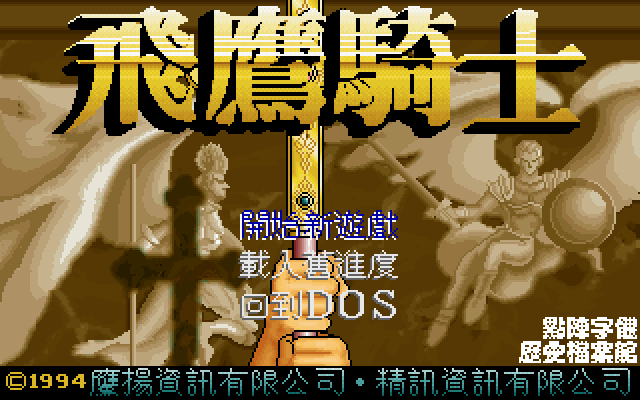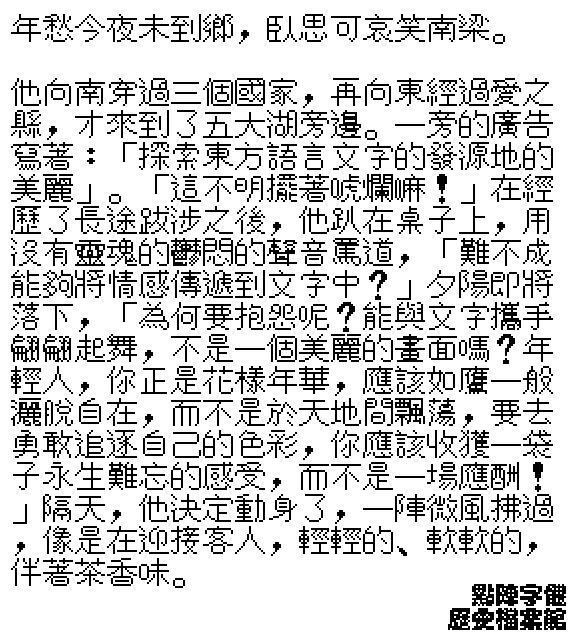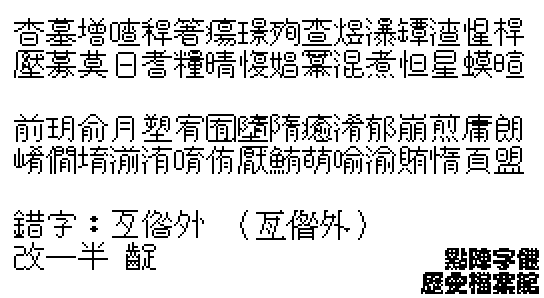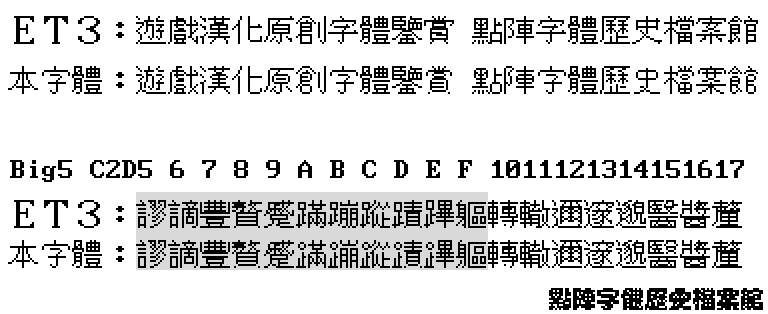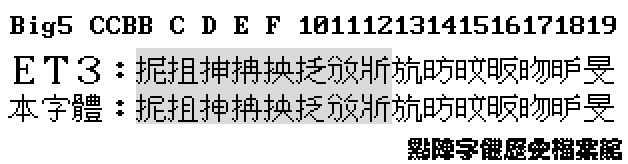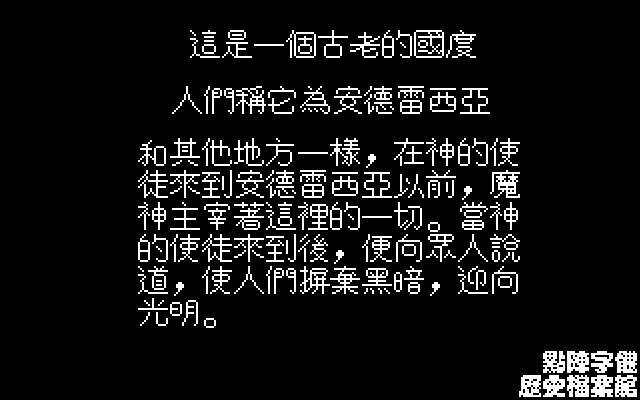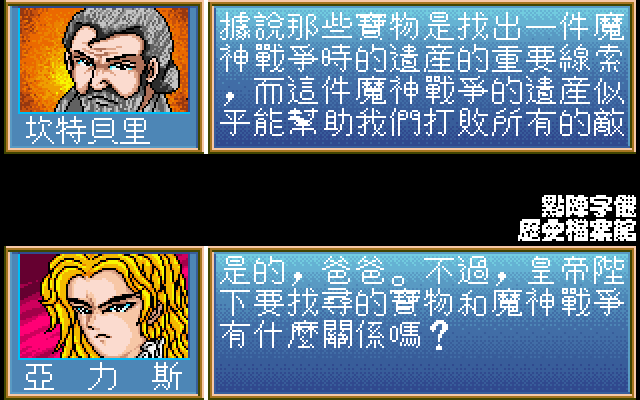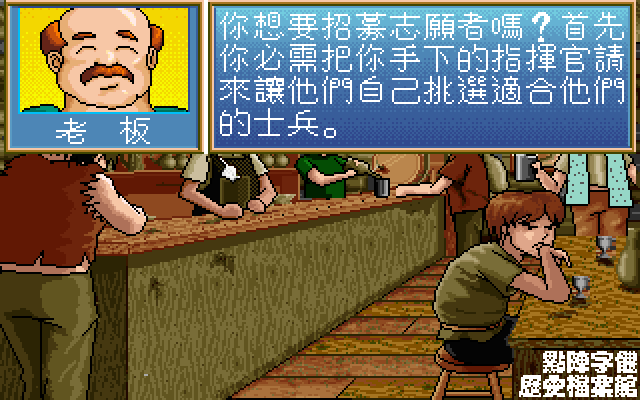
早安,這是小型欄目《遊戲漢化原創字體鑒賞》,關注於早期只在遊戲漢化中出現的點陣字體。
此欄目第三款要介紹的字體,是鷹揚/精訊於1994年後推出的漢化或原創遊戲所採用的字體。風格上是至今都少見的16Px圓體。
圖:採用此字體的遊戲。
猜測這款字體在誕生之初就是在該公司的所有產品上使用,所以一經亮相就是可廣泛使用的狀態了。該字體整體感覺偏扁,常用字中能展現圓角的地方幾乎都弄了,特別是日、目、月等字選擇橫不接豎也為字體增添了特色。可惜偶有錯字及圓一半的字。
圖:字體樣張。
圖:日、月等部件橫不接豎。
經過觀察,這款字體是以ET3 16Px字體為底稿進行改造的。並且應該是依照Big5的順序改造的,因為改到次常用字的前幾個字斷斷續續地就停了(基於時間效益次常用字不處理沒什麼問題)。也很可惜常用字到筆畫很多的部分也停了。
圖:與ET3字體比較。
圖:與ET3 16Px對比,大約只做到“斨”字。
不過非常非常可惜,這款字體水平稍為低劣,筆划多的常用字也並未完全圓體化,骨架也大受ET3影響,風格多變,也有些字只圓體了一半,難以大量長篇使用。個人認為己經會在遊戲中影響閱讀。
圖:實機效果演示。